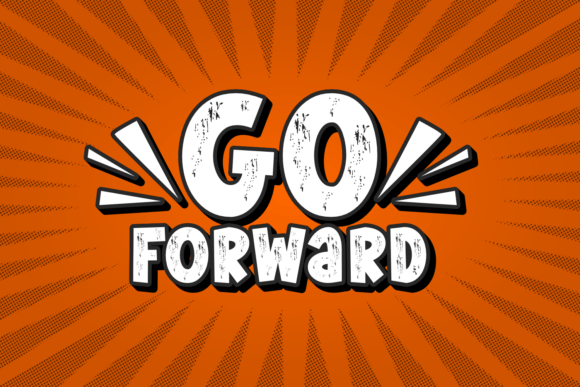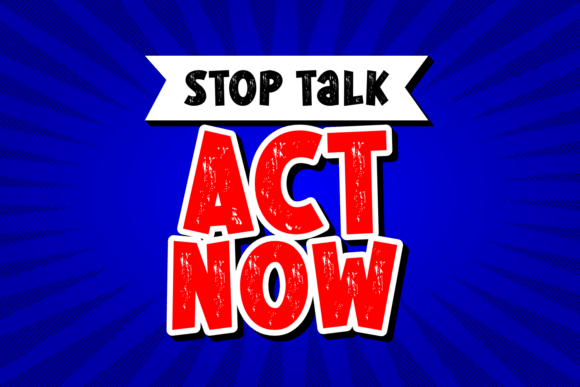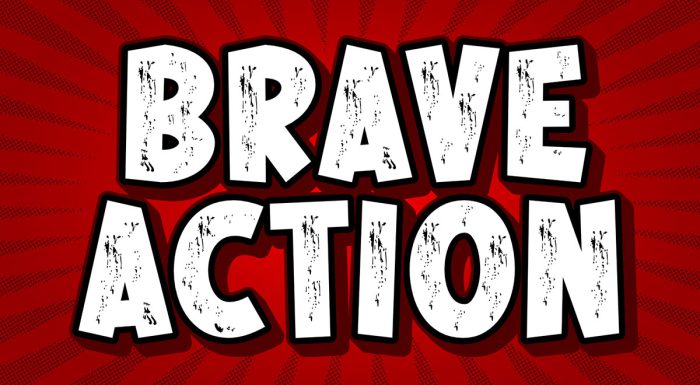
فونت Brave Action انگلیسی
دانلود فونت Brave Action انگلیسی Font برایو اکشن |
| ⭐ مجموعه فونت | دانلود فونت انگلیسی اقدام شجاعانه Font Brave Action |
| ⭐ توضیحات | Brave Action یک فونت نمایشگر قدرتمند با ظاهری پریشان است. این شخصیت های قوی برای ایجاد تایپوگرافی الهام بخش عالی هستند. از آنها برای افزودن شخصیت و استایل به پوسترها، نقل قول ها، جلدها، تیترها، تی شرت ها و موارد دیگر استفاده کنید. |